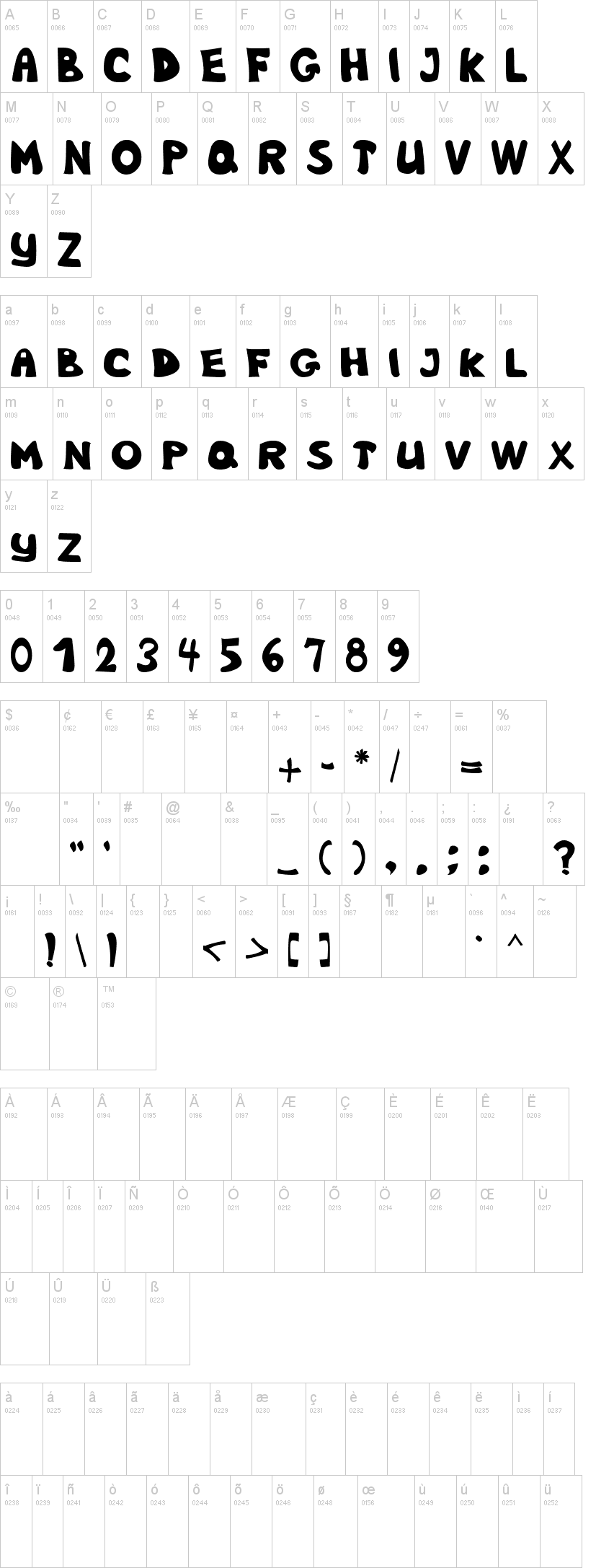
Nb Obese
Nb Obese 是一款卡通类型的英文字体,由Nathan Brown设计,是一款有趣的、轻松的字体,可以用于各种娱乐性的场合,如海报、标识、T恤等。Nb Obese的字体设计风格独特,字形宽大而圆润,拥有趣味性和可爱性,可以为您的设计增添趣味,是一款适合创作娱乐场合的字体。
Nb Obese是一款非常不错的手写艺术字体,具有很好的视觉感,适合于文化类的宣传设计、商业类品牌的广告和产品包装设计以及个性化文字排版等较多场景。
Nb Obese字符映射图